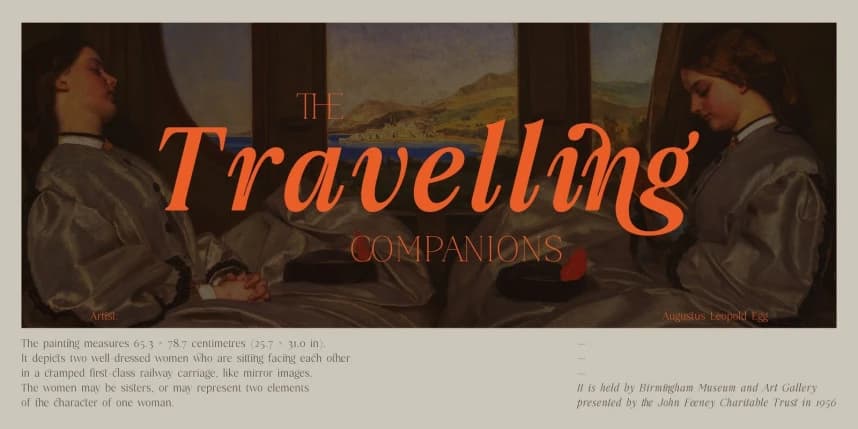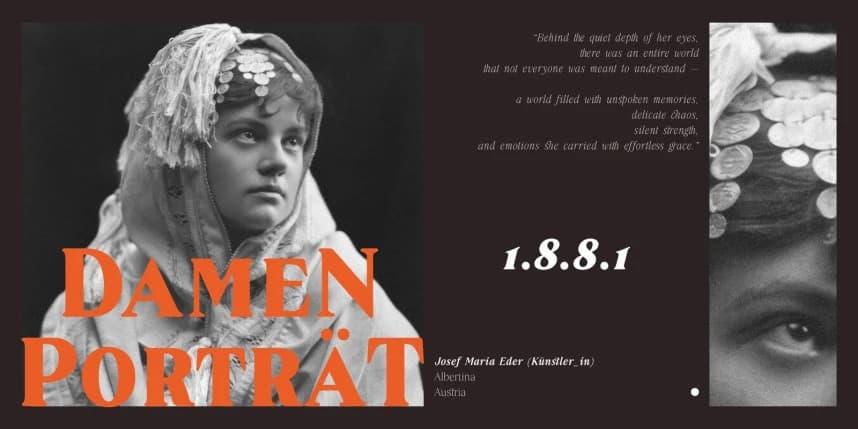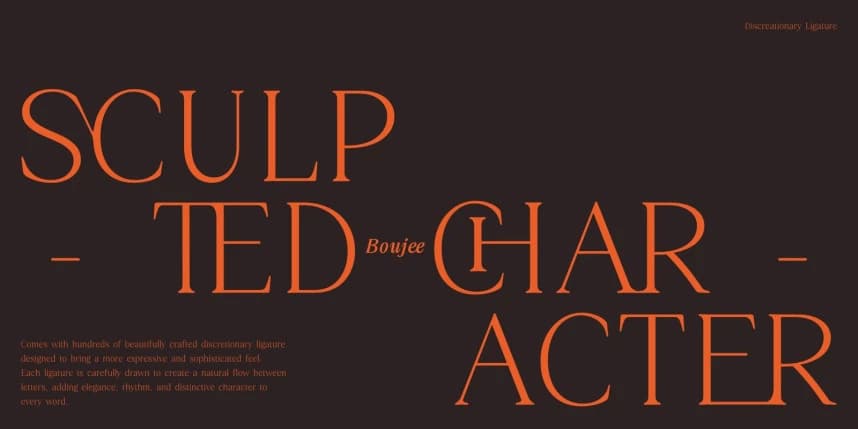
Boujee Font
Boujee Font, eski tipografi zarafeti, vintage editoryal tasarımlar ve zamansız lüks estetiğinden ilham alan şık bir serif yazı tipidir. Zengin kontrast ve zarif detaylarla tasarlanan Boujee, hem nostaljik hem de sofistike bir hava veren rafine bir kişilik sunar.
- Serif Yazı Tipi
Boujee Font, eski tipografi zarafeti, vintage editoryal tasarımlar ve zamansız lüks estetiğinden ilham alan şık bir serif yazı tipi. Zengin kontrast ve zarif ayrıntılarla tasarlanan Boujee, hem nostaljik hem de sofistike bir his veren rafine bir kişiliğe sahiptir.